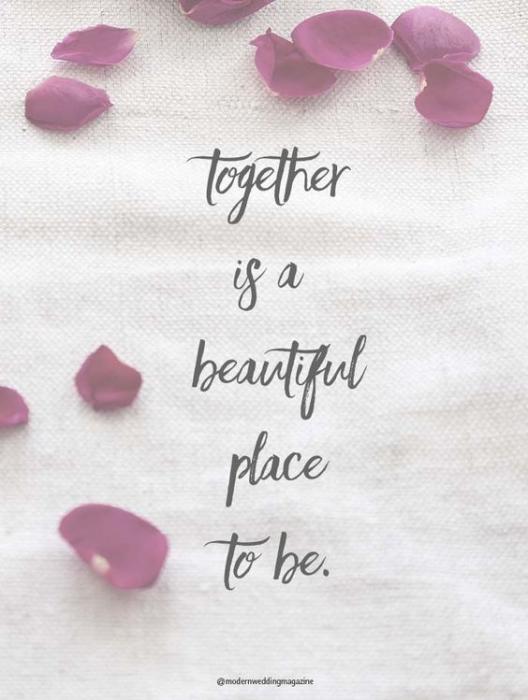
Handschrift gesucht
wisst ihr welche Font das ist?
Also auf alle Fälle einer, der entweder mit veralteter Technik benutzt wurde oder selbst veraltet ist.
Moderne Fonts, deren Texte wie handgemacht aussehen sollen, bieten mehrere Formen sowohl für mehrfach auftretene (Einzel-)Buchstaben als auch speziell gestaltete Formen für problematische Buchstabenkombinationen an. Hier fallen besonders die vier t auf, die alle identisch aussehen. Das würde in einem handgeschriebenen Text nie so aussehen. Deshalb wirkt diese Gestaltung mindestens unbewusst merkwürdig und (auf Profis) billig.
Kurz und gut: verschwende nicht weiter deine Zeit nach der Suche nach genau diesem Font, sondern suche lieber einen mit ähnlicher Anmutung, der moderne Techniken nutzt.